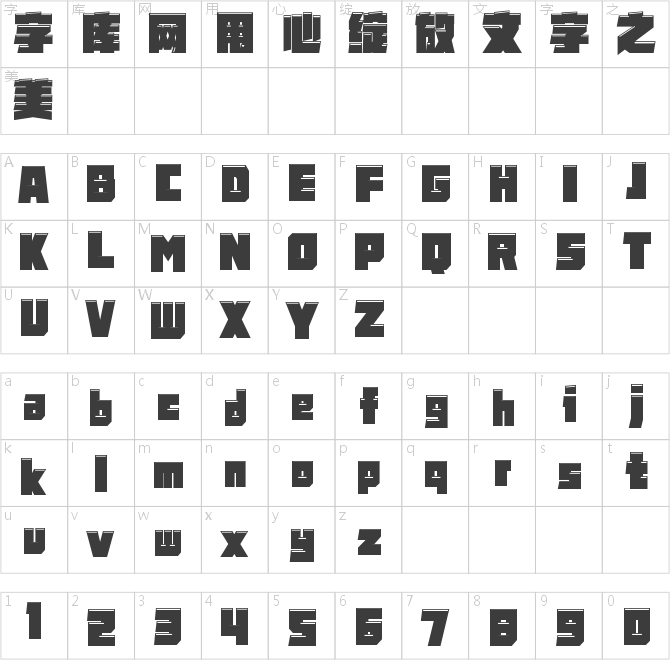
銳字機甲洪荒超級光字體下載
在超級黑的基礎(chǔ)上,將筆畫內(nèi)部加入梯形的高光線條,更具立體感。在鉤筆畫處加入傾斜高光,根據(jù)筆畫調(diào)整位置與方向,更具識別性。銳字機甲洪荒超級光字體字庫是一款讓人賞心悅目、百看不厭的中文字體,適合各類廣告和產(chǎn)品包裝設(shè)計應(yīng)用,字體大小1.33MB,格式為ttf字體,上傳用戶是……西央,作者/版權(quán)方為銳字潮牌